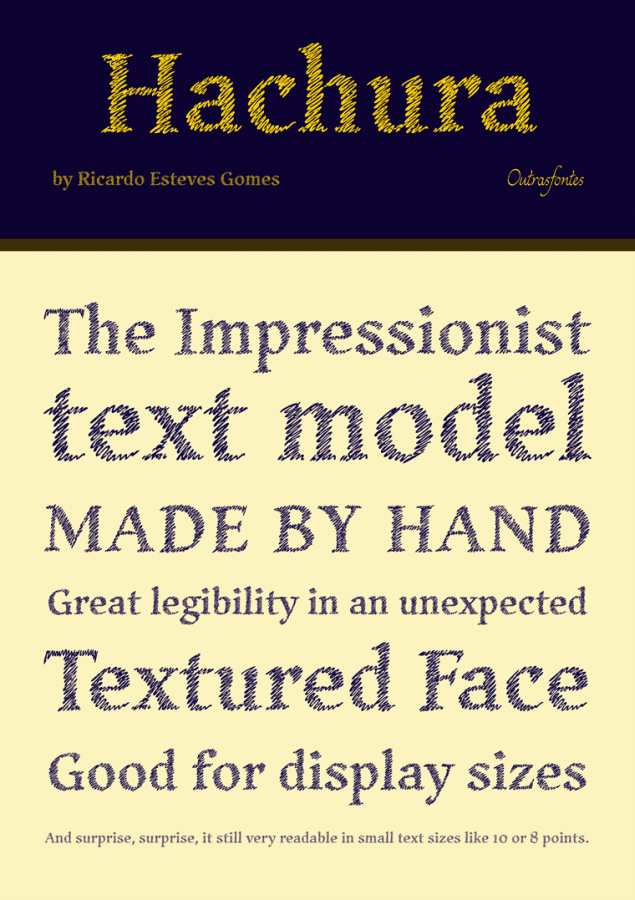
Vermutlich liegt’s an meiner großen Sympathie für die Impressionisten, daß ich die Hachura sofort interessant finde. In großen Größen wird sie m.E. etwas unruhig, aber gerade in mittleren Größen hat sie, wie ich finde, wirklich eine »impressionistische« Textur.
Hachura is an impressionist typeface designed by Ricardo Esteves Gomes. Its general proportions are based on the garalde models, with traditional roman serifs. It was initially made by hand using a drawing technique to create a font that simulates the unfinished aspect of a work in constant progress. This textured face is useful for display sizes, making a very visible presence. Because of its basic dimensions and careful distribution of black and white, it still also very readable in text sizes like 10 or 8 points.
hat was. kann man aber auchleicht selber machen.
einfach im illustrator unter effekte -> stilisierungsfilter -> scribble auswählen
und mit den einstellungen herumspielen.
hat was. kann man aber auchleicht selber machen.
einfach im illustrator unter effekte -> stilisierungsfilter -> scribble auswählen
und mit den einstellungen herumspielen.
Für so ein Projekt wäre es sicher sehr interessant gewesen, zahlreiche alternative Buchstaben zu schaffen, das hätte die ganze Sache noch mal richtig gut gemacht und auch die »einfache Erstellung« erschwert. Die Buchstaben haben gerade in der größeren Ansicht ja doch einige Unregelmäßigkeiten, die sehr repetitiv erscheinen. Eigentlich schade drum.
Ohne jetzt aber wirklich selber in AI rumgespielt zu haben: Wie gut und schnell bekommt man da eine Schrift hin, die einen wirklich impressionistischen Charakter hat? Mit den artistischen Filtern in Photoshop habe ich durchaus öfter mal herumgespielt. Da kann man natürlich auch seinen eigenen »van Gogh« kreieren, den echten expressionistischen Charakter trifft man aber doch nur sehr selten! :tutor: :D
Wenn schon selbst basteln, dann würde ich das lieber per Hand machen als mich mit Kunstfiltern rumzuärgern:
1. Alphabet der Lieblingsschrift dreimal in 64 pt ausdrucken.
2. Auf Layoutpapier (Konturen bluten nicht aus) auf dem Lichttisch oder auf Transparentpapier drüberschraffieren.
3. Mit mindestens 600 dpi als Bitmap einscannen und im Fotoshop den Staub rausfiltern (max. 2 Pixel).
4. Im Photoshop, Freehand, Illustrator oder sonstwo "tracen", also automatisch in Vektoren umwandeln.
5. Weiterverarbeitung (also in einen Font mit Alternativzeichen etc. umbauen) je nach Möglichkeit.
Wie gut und schnell bekommt man da eine Schrift hin, die einen wirklich impressionistischen Charakter hat?
ergebniss nach einer minute. probiers mal aus, ist wirklich easy.
@ norbert:
ich kann den text aber danach noch editieren, du musst ihn neuzeichnen :)
Schon klar, aber filtern ist mir zu steril :wink:
ergebniss nach einer minute. probiers mal aus, ist wirklich easy.
Ich weiß das, ich verstehe schon was Du mir sagen willst und will auch die Hachura überhaupt nicht über den grünen Klee loben. Aber Deine Beispiele haben mit der Hachura so viel gemein wie ein Kuckuck mit einem Känguru und das Gefühl »Impressionismus« strahlen sie schon gleich gar nicht aus. Das ist es doch, was ich sagen wollte! Klar, in irgendwelche Striche kann ich das auch verwandeln, habe gestern auch noch etwas rumprobiert. Ist wirklich einfach und recht schnell bewerkstelligt. Das wirkt dann aber eben einfach schraffiert und nicht impressionistisch – gerade Dir als Designer müßten die Unterschiede doch grell ins Gesicht springen? :? :!:
was verstehst du denn unter 'impressionistisch'?
klar sind da unterschiede drin aber ich denke mit etwas feinschliff bekommt
man diese auch feinheiten auch hin. kommt halt drauf an was du für ein ergebniss willst.
was verstehst du denn unter 'impressionistisch'?
Ich verbinde viel mit dem Begriff »impressionistisch«. Sehr typisch für die impressionistischen Gemälde ist doch z.B. die feine Pinselführung, die Darstellung von Details mit Hilfe vieler, beinahe flüchtiger Pinselstriche. Einen ähnlichen Effekt findet man auch in der impressionistischen Musik, eine Klangmalerei, in welcher Details durch ungemein virtuose und schnelle Phrasen »gezeichnet« wurden. Die Details bekommen dadurch einen für den Impressionismus typischen, etwas »verwischten«, flüchtigen Charakter, die Gesamtkunstwerke sind ungeheuer dynamisch. Der Impressionismus war ja um die Jahrhundertwende (19./20. Jhd), also quasi bereits in der Mitte der Industriellen Revolution und in Malerei, Musik aber auch Photographie kann man gut ablesen, daß die damaligen Künstler der Technik extrem aufgeschlossen gegenüber standen. Der Mensch wird sehr als Einheit mit der Natur wahrgenommen und Technik als Machwerk des Menschen ist nicht diabolisch sondern löst Begeisterung aus, die Kunstwerke haben dadurch einen ziemlich heiteren und aufhellenden Charakter.
Das Licht spielt eine weitere wichtige Rolle in impressionistischen Kunstwerken. So wurde z.B. so gut wie keine schwarze Farbe eingesetzt, da die impressionistischen Maler erkannt haben, daß schwarz in der Natur nur selten vorkommt. Schattenwürfe etc. wurden durch dunkles blau, dunkles braun oder auch grau dargestellt. Zusammen mit der detaillierten Lichtführung, der Freude an der Darstellung des Lichtes macht dieses Fehlen der sehr dunklen Farben die Bilder farbkräftig und licht.
Und genau dies finde ich persönlich in der Hachura wieder. Das schwarz, die Schwere der Buchstaben durch eine reine Füllfarbe ist zurückgenommen, die Details sind zwar da, werden aber durch die Schraffur ähnlich der flüchtigen Pinselführung der Impressionisten dynamischer und ähnlich »flüchtig« wie die Details in den impressionistischen Gemälden. Es ist nicht einfach nur eine Schraffur der Buchstaben, es ist die Wiedergabe der Details durch eine bestimmte Technik. Die Hachura erscheint mir warm, licht und leicht.
Dada wäre das hier:
... ist ja auch eigentlich Mondrian (Konstruktivismus), was mein Namensvetter da fabriziert hat ...
Aber, aber, papperlapapp! Von wegen … dort steht in voller Transparenz ein wortloses Lautgedicht, von Hugo Ball einst vorbegründet: "Was wir DaDa nennen, ist ein Narrenspiel aus dem Nichts, in das alle höheren Fragen verwickelt sind."
Ich versuch’s mal mit Surrealismus …